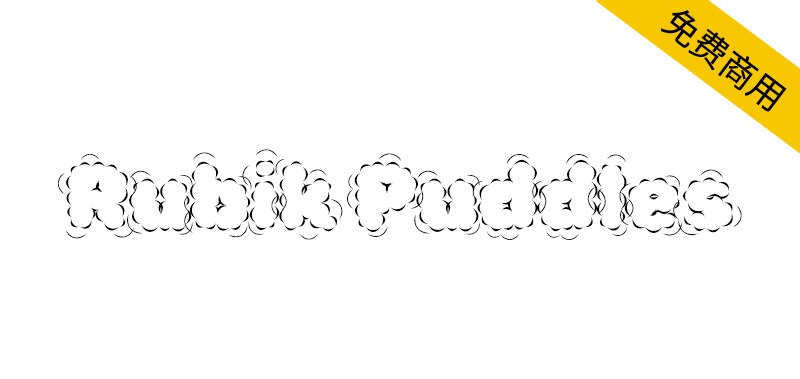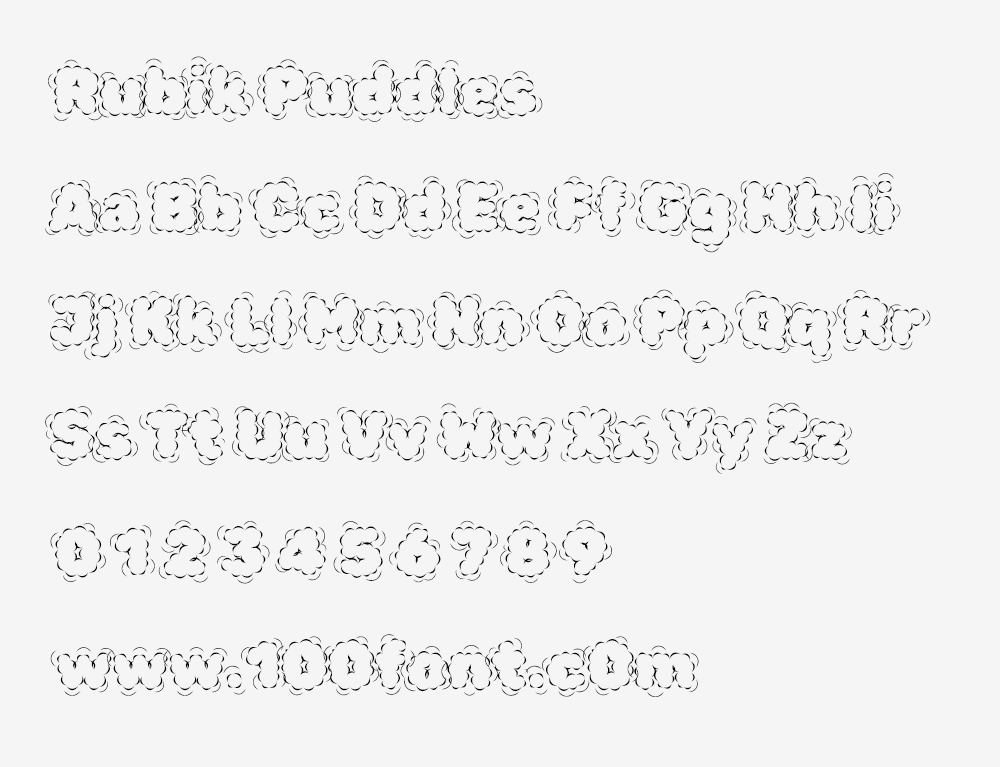
RubikFilteredFonts是基于Hubert & Fischer,Meir Sadan和Cyreal的GoogleFontRubik的原始脚本生成设计。用于生成它的代码可以在https://github.com/NaN-xyz/Glyph-Filters中找到。
RubikFilteredFonts are original, script-generated design based on the GoogleFontRubikbyHubert & Fischer,Meir SadanandCyreal. The code used to generate it can be found athttps://github.com/NaN-xyz/Glyph-Filters.